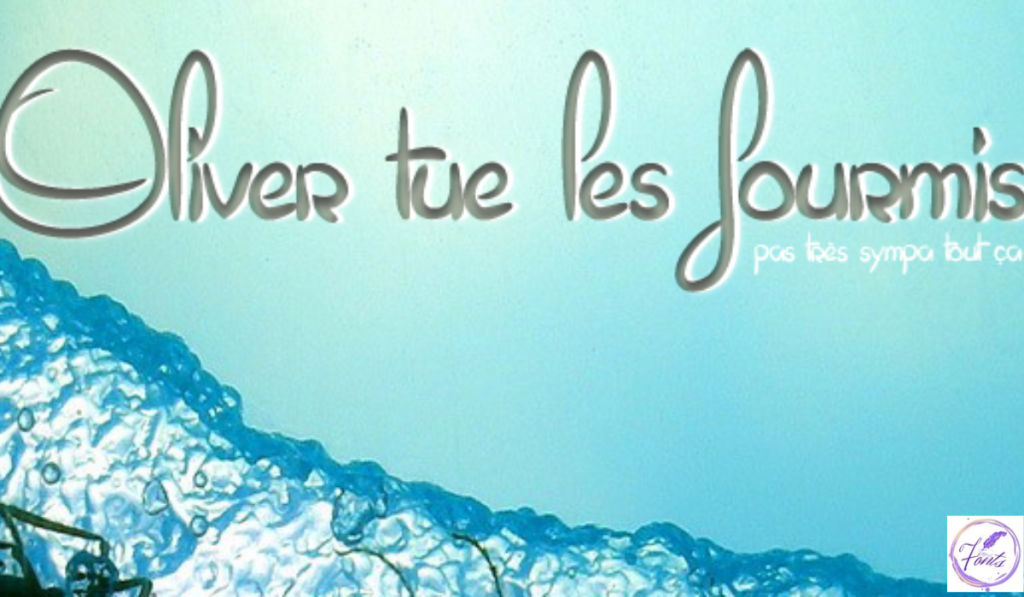
Font HLT Oliver Tue Les Fourmis Việt hóa
Tác giả: Thomas Boucherie
Ngày phát hành: 2022
Bộ Font: HLT
Phân loại: Độc đáo, nghịch ngợm
Kiểu chữ: Viết tay
Độ dày: Oliver tue les fourmis
Font HLT Oliver Tue Les Fourmis là một font chữ độc đáo và đầy sáng tạo của bộ font HLT, được thiết kế bởi nhóm thiết kế HLT vào năm 2021. Font này mang phong cách hiện đại và vui nhộn, với các đường nét mềm mại và dễ đọc. Đặc biệt, font hlt oliver tue les fourmis hỗ trợ đầy đủ các ký tự tiếng Việt, giúp bạn dễ dàng sử dụng trong các dự án thiết kế từ in ấn đến kỹ thuật số mà không gặp bất kỳ vấn đề nào về ký tự.